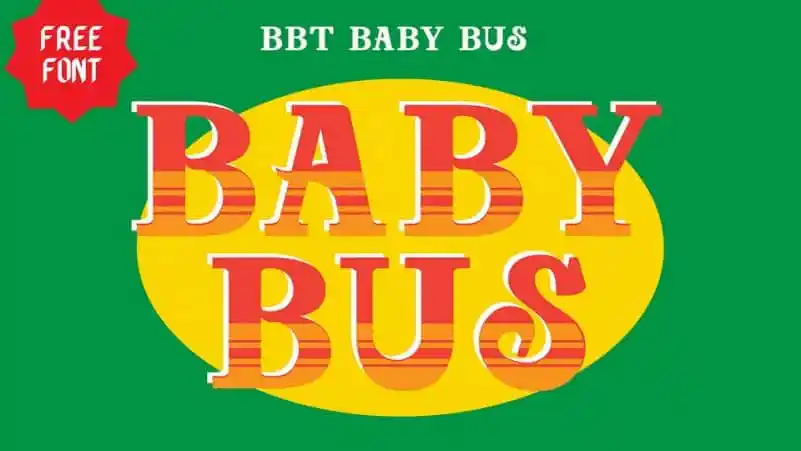
A Baby Bus Slab Serif Font é uma opção moderna para projetos de design que buscam trazer uma atualização contemporânea aos textos. Suave e elegante, mas com um toque aventureiro e vibrante, ela se assemelha à tipografia em letras de palavras coloridas do projeto Baby Bus de Cavite. Essa fonte é perfeita para criar um design emocionante e envolvente, que vai capturar a atenção dos usuários, sem sacrificar o respeito pelo texto. Cada detalhe da Baby Bus Slab Serif foi projetado com precisão para complementar as letras vibrantes do Cavite’s Baby Buses, oferecendo uma combinação única de elegância e energia. Para aqueles que buscam uma fonte moderna, versátil e incrivelmente atraente, esta é uma opção perfeita. Como parte da coleção 99designs, o público pode encontrar uma fonte leve para usar em sites, logotipos ou materiais de marketing com um toque nostálgico que remete à infância. A versão gratuita inclui todas as letras maiúsculas, criando uma opção econômica e versátil para aqueles buscando incorporar o design carismático do Baby Bus em seus projetos.